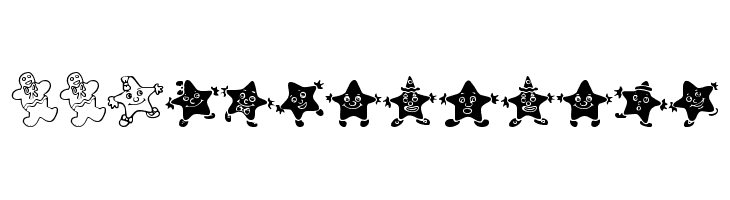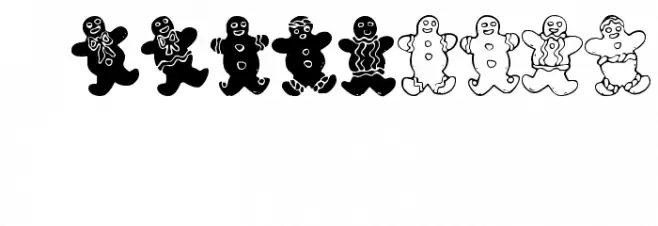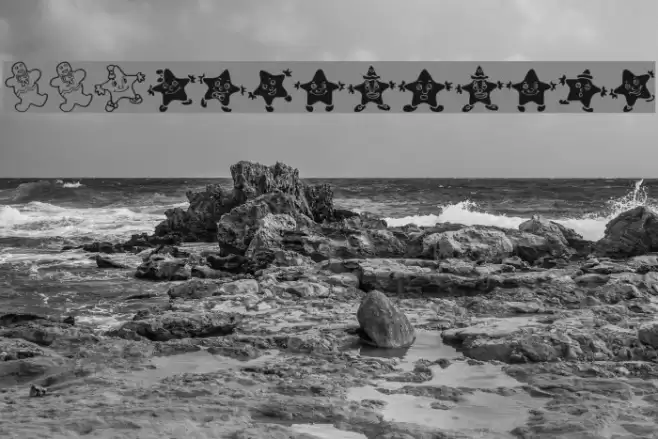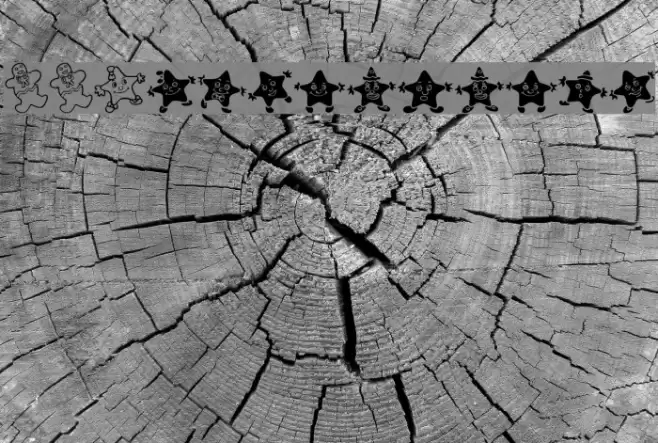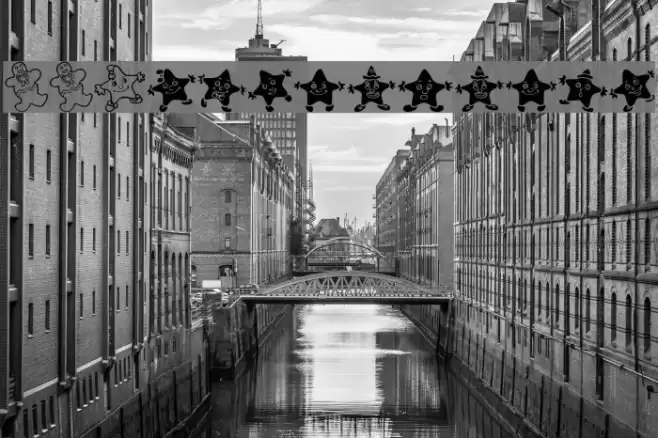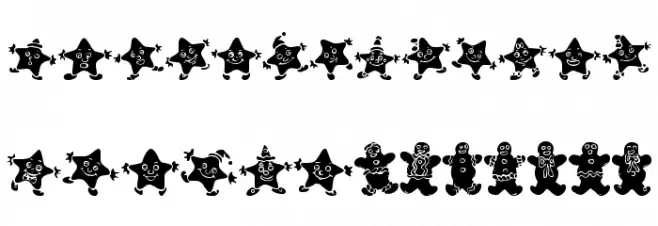
WWGingerbread Font
| Style général | Whimsical and festive |
| Cas d'utilisation | Decorative elements for holiday designs. |
| Projets proposés | Ideal for holiday-themed decorations, greeting cards, or festive banners. |